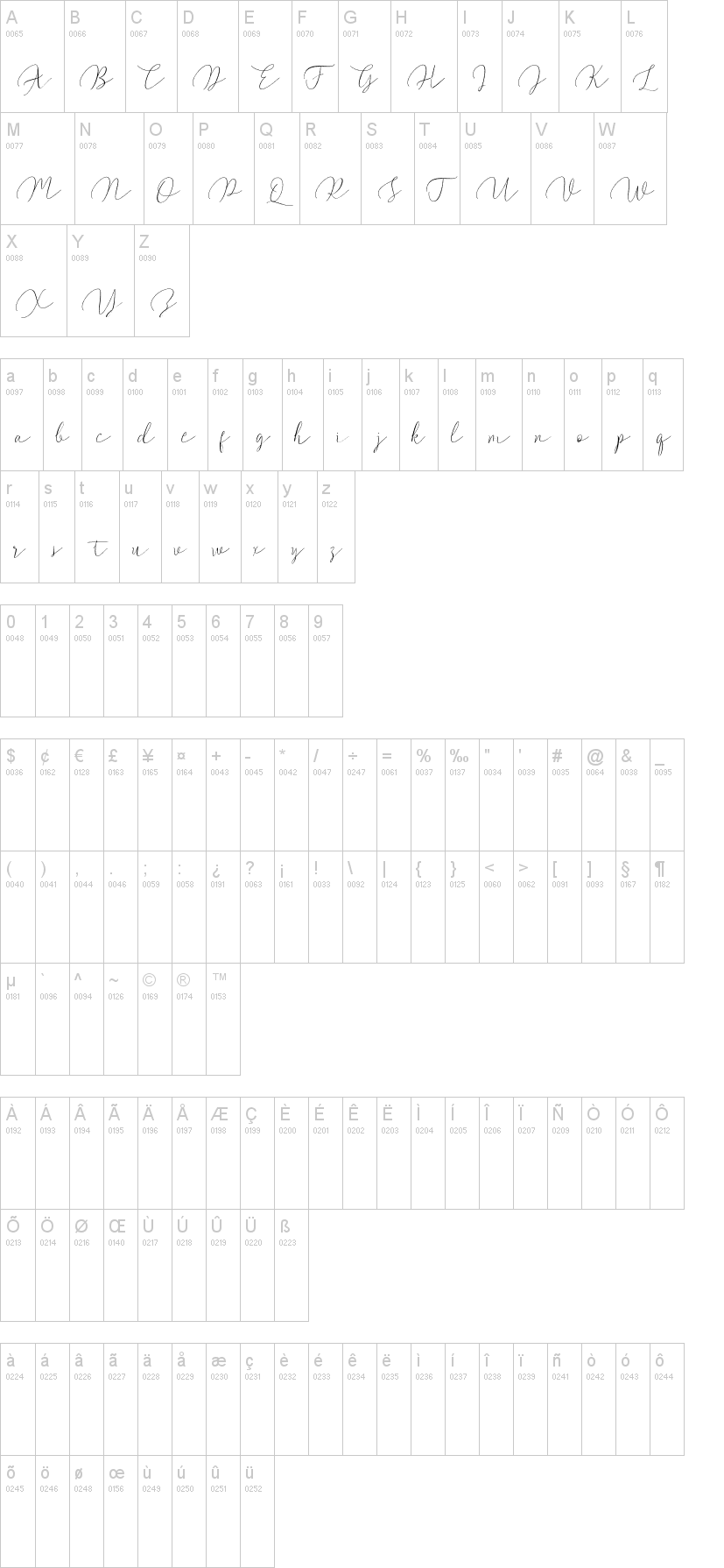
Walty Script
Walty Script 是一款漂亮的手写字体,它采用了精致的曲线,细腻的笔画,以及精心设计的字形,使它看起来既有趣又充满活力。Walty Script 字体的特点是它的曲线和自然的笔画,使它看起来更加自然,可以用于创建精致的文字效果。它适用于各种场合,如标题、标签、标语、卡片等。Walty Script 字体可以帮助您创造出精致、有趣、有节奏感的文字效果,给您的设计带来活力与灵动。
Walty Script是一款非常不错的手写艺术字体,具有很好的视觉感,适合于文化类的宣传设计、商业类品牌的广告和产品包装设计以及个性化文字排版等较多场景。
Walty Script字符映射图